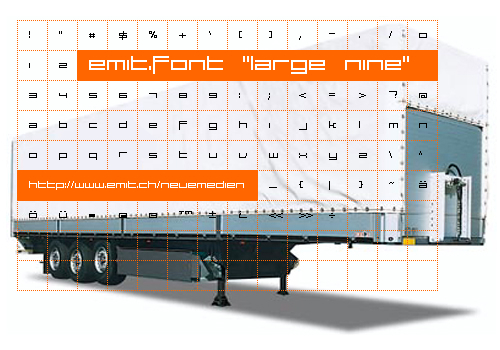
Large 9 von Emit Neuemedien, entworfen im Jahr 2000, ist eine kostenlose Bitmap-Schrift mit einer strikten Pixel-Raster-Struktur und quadratischen, offenen Formen. Die Buchstaben behalten durchgehend den gleichen modularen Rhythmus bei, wodurch die Schrift codiert und mechanisch wirkt, ohne dabei gedrängt zu sein.
Large 9 eignet sich hervorragend für Interface-Labels, Arcade-Menüs, Software-Splash-Texte, Poster-Captions und Zine-Cover, die einen Low-Resolution-Look benötigen. Die abgestuften Formen machen sie zudem nützlich für kurze Branding-Elemente, Beschriftungsleisten und experimentelle Editorial-Layouts, bei denen das Pixelmuster visuell genauso viel leistet wie die Wörter selbst.